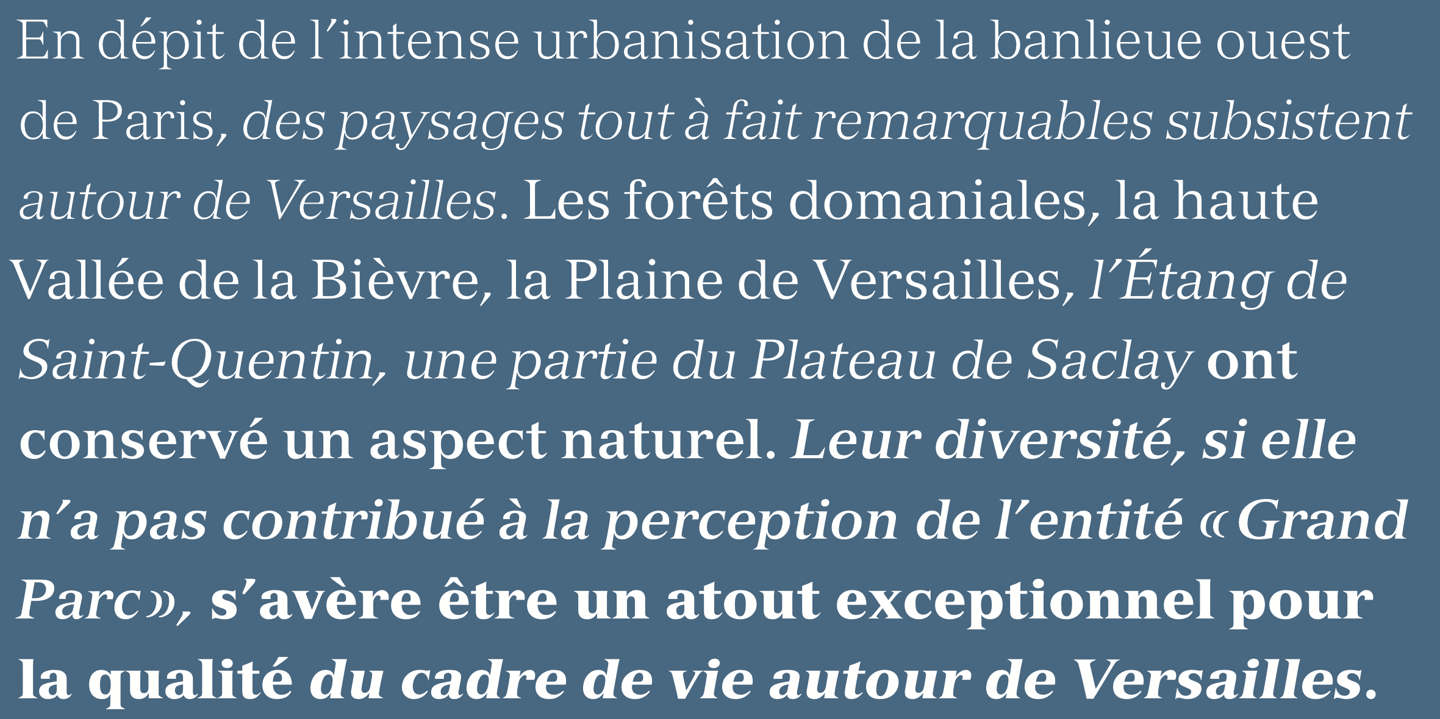
Die Versailles ist eine Antiqua-Familie von Adrian Frutiger und erschien in den 1980er-Jahren als Fotosatzschrift über Linotype. Die Schriftfamilie besteht aus vier Strichstärken mit zugehörigen Kursiven.
Die Schriftfamilie ist heute digital in einer erweiterten Pro-Version über Linotype verfügbar, jedoch im Gegensatz zu Fotosatzversion nur noch mit einem Ziffernsatz.